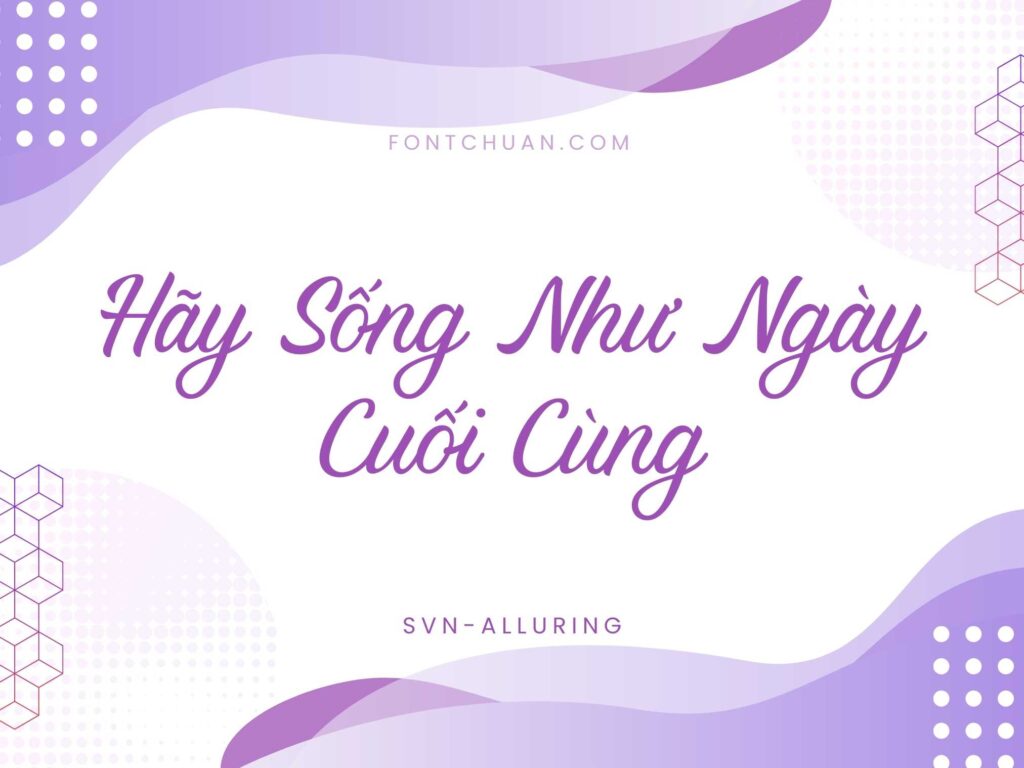
Font SVN Alluring Việt Hóa
Tác giả Font: 50Fox Team
Alluring là một font chữ mang phong cách sang trọng và hiện đại, được thiết kế bởi 50Fox Team. Font này có đường nét mềm mại, tinh tế nhưng vẫn giữ được sự mạnh mẽ, phù hợp cho nhiều mục đích sử dụng như thiết kế logo, nhãn hiệu, tiêu đề, bao bì sản phẩm và thiệp mời. Với hơn 200 ký tự hỗ trợ đa ngôn ngữ, Alluring là một lựa chọn tuyệt vời cho các nhà thiết kế muốn tạo ra những tác phẩm chuyên nghiệp và sáng tạo. Font đã được Việt hóa để hỗ trợ tiếng Việt bởi Styleno.1 Fonts, đồng thời hỗ trợ nhiều ngôn ngữ khác, giúp mở rộng phạm vi sử dụng trên toàn cầu. Font này được thành viên của Font Chuẩn sưu tầm và chia sẻ, đáp ứng nhu cầu của bạn đọc và ứng dụng thực tế vào các dự án thiết kế.
Đặc điểm thiết kế của Alluring bao gồm cấu trúc chữ tinh tế, đường nét thanh thoát và độ cân đối hoàn hảo, giúp tạo nên sự thu hút và ấn tượng. Font này phù hợp cho các ứng dụng như thiết kế logo, nhãn hiệu, tiêu đề sách, bao bì sản phẩm và áp phích. Các ngành nghề phù hợp bao gồm quảng cáo, thương hiệu, thời trang và thiết kế sáng tạo.